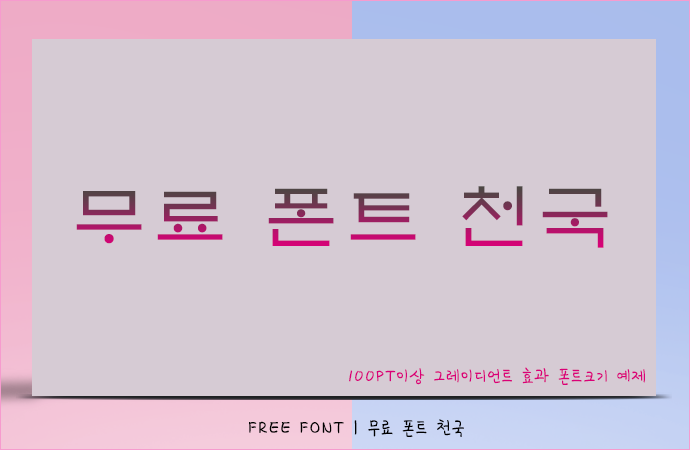
세종대왕의 숨결이 느껴지는 EBS훈민정음체 한글 폰트
EBS훈민정음체 폰트 정보
EBS훈민정음은 훈민정음 정체와 더불어 목판으로 제작된 해례본체의 기본형과 주요특징을 유지하면서 단순화한 획과 선으로 디자인되어 글꼴의 가독성을 높이고 크기를 줄여 모바일과 웹 환경에 최적화 되어있습니다. 개인 및 기업에서 상업적인 용도로 누구나 자유롭게 사용 가능한 무료 서체입니다.
EBS훈민정음체 폰트 # 미리보기
EBS훈민정음체, 12~80PT 크기로 가독성을 테스트 해본 폰트
EBS훈민정음체, 100PT 크기 이상으로 작업한 오버레이 효과를 적용한 폰트
EBS훈민정음체, 100PT 크기 이상으로 그레이언트를 효과를 적용한 폰트